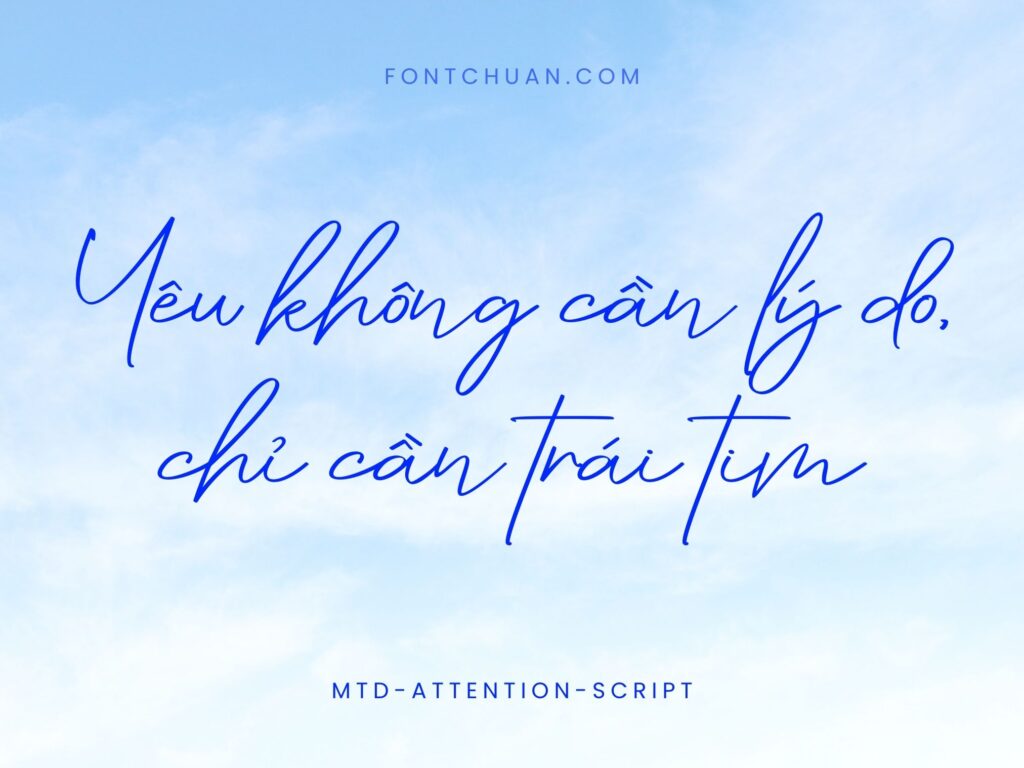
Attention Script là một kiểu chữ viết tay hiện đại, được thiết kế bởi Menk Type và phát hành vào khoảng năm 2017. Với các nét chữ uyển chuyển và tinh tế, Attention Script mang lại cảm giác thanh lịch và thân thiện, phù hợp cho nhiều dự án thiết kế sáng tạo.
Phiên bản Attention Script đã được Việt hóa bởi Mộc Hạ, hỗ trợ đầy đủ tiếng Việt cùng hơn 64 ngôn ngữ khác như Anh, Pháp, Tây Ban Nha, Đức và Ý, mở rộng khả năng ứng dụng trong thiết kế đa ngôn ngữ. Font này đã được thành viên Font Chuẩn sưu tầm và chia sẻ, đáp ứng nhu cầu của cộng đồng thiết kế. Với thiết kế bao gồm các ký tự viết tay mềm mại và đa dạng, Attention Script phù hợp cho các ứng dụng như thiết kế logo, thiệp mời, bao bì sản phẩm và các ấn phẩm quảng cáo. Các ngành nghề như quảng cáo, giáo dục, công nghệ và ẩm thực có thể tận dụng font này để tạo ra thiết kế ấn tượng và thu hút.